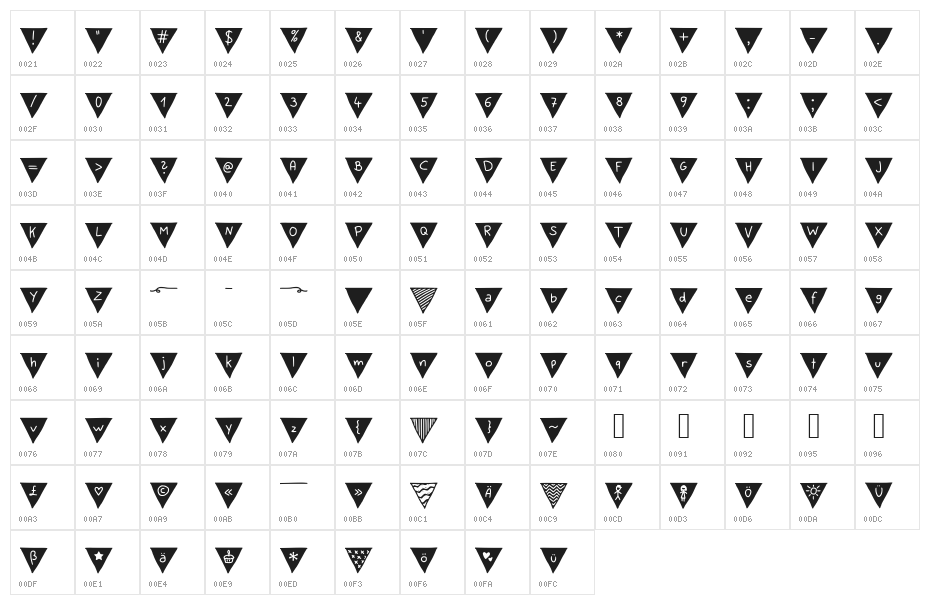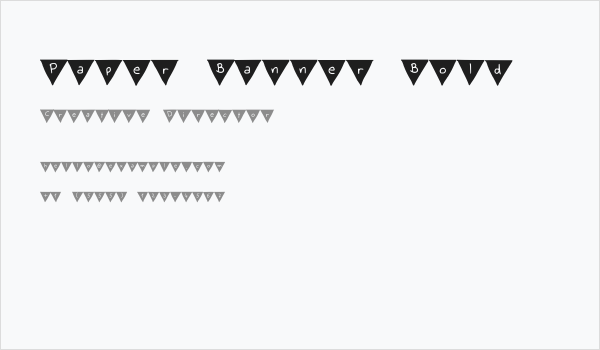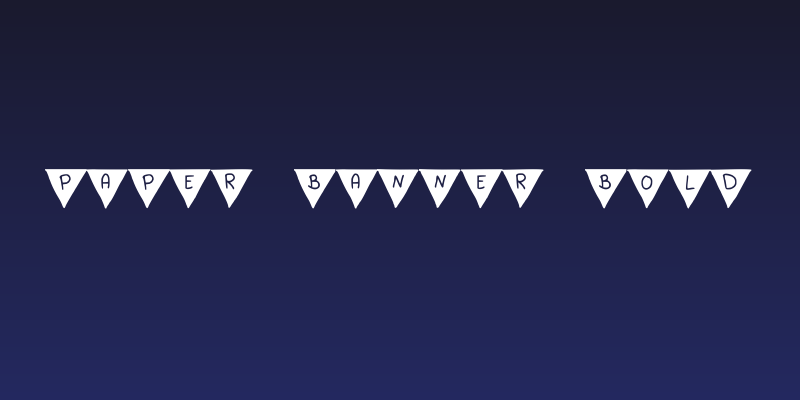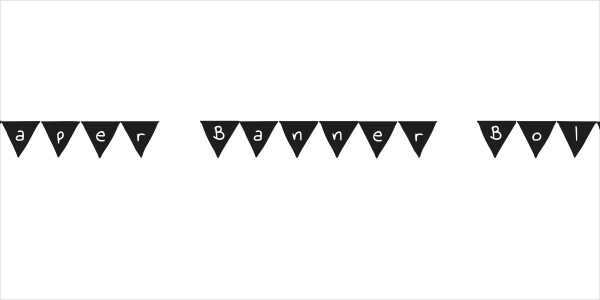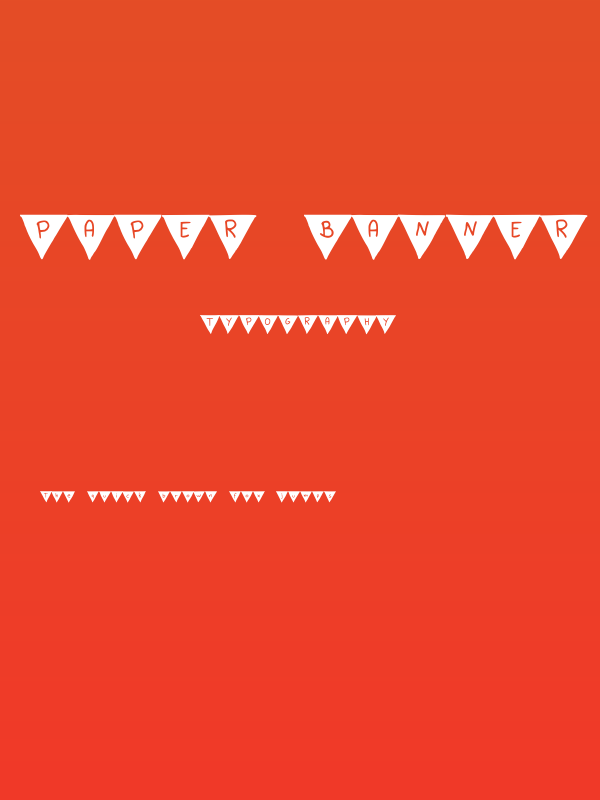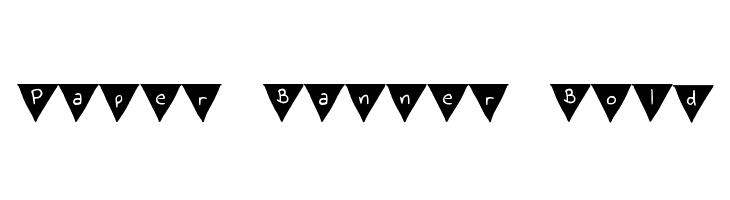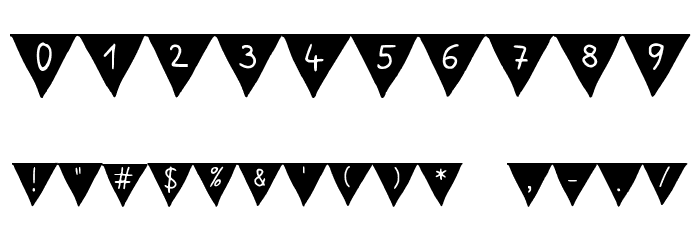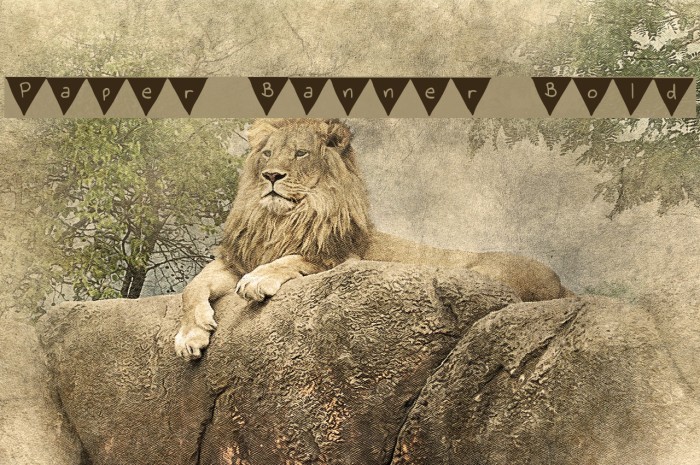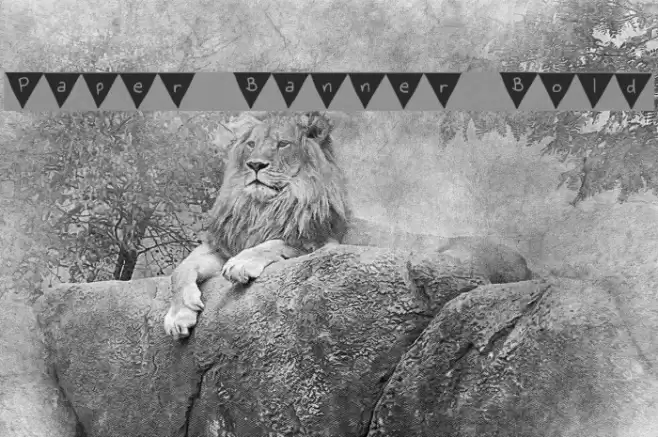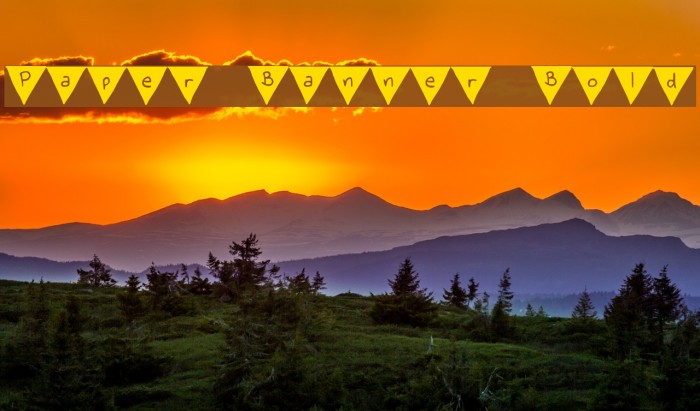
Paper Banner Bold Font
Acest font include 137 caractere. Clic pe orice caracter pentru detalii.
| Proiecte propuse | Ideal for party invitations, banners, festive posters, and children's event materials. |